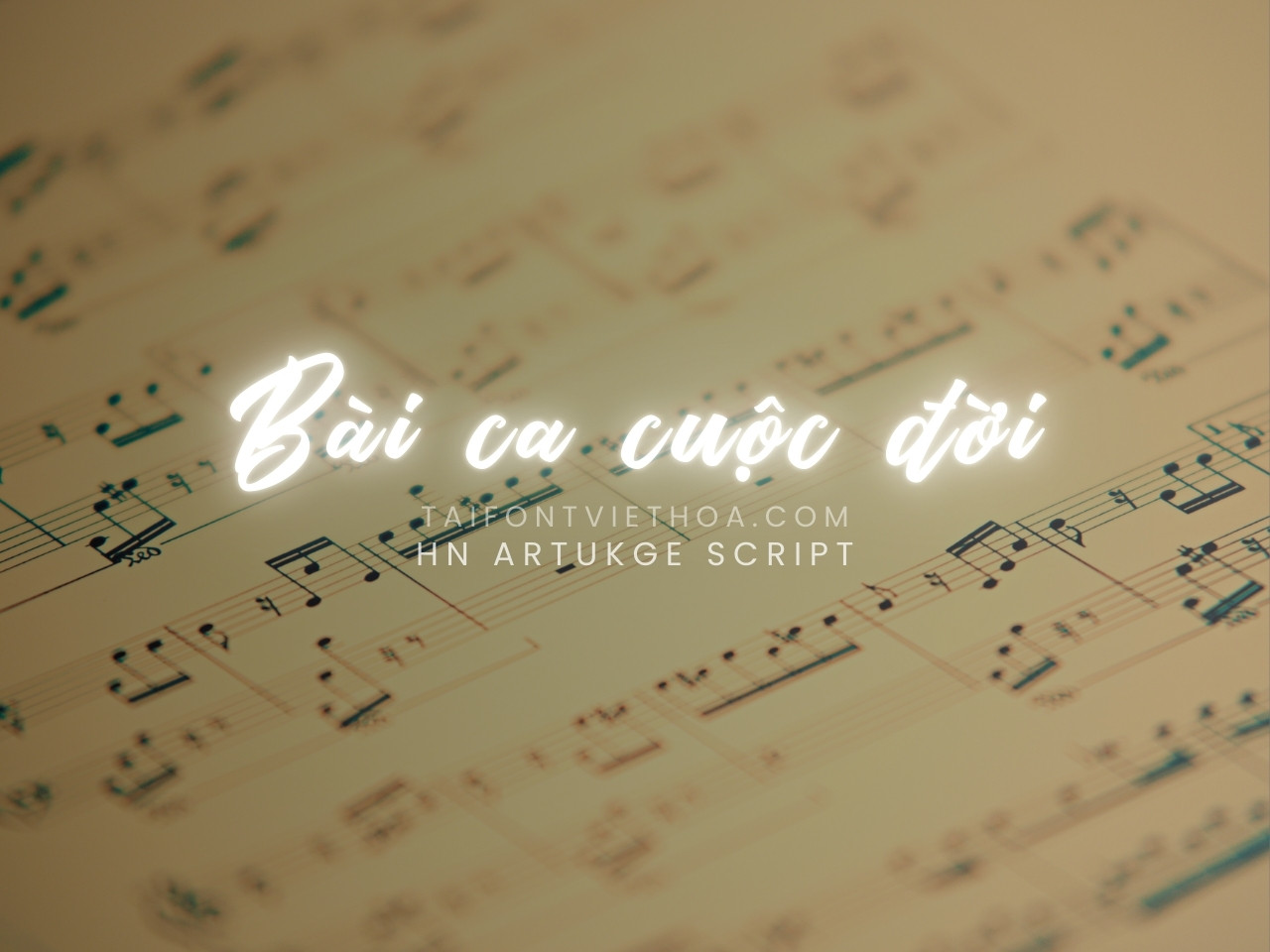
Giới thiệu font Artukge Script – Vẻ đẹp viết tay bay bổng từ Font Fabric
Artukge Script là một font chữ viết tay đầy cảm xúc được phát triển bởi Font Fabric Free – đơn vị thiết kế nổi tiếng chuyên cung cấp các font sáng tạo miễn phí chất lượng cao. Với kiểu dáng uốn lượn, mềm mại và mang tính cá nhân hóa cao, Artukge Script nhanh chóng chiếm được cảm tình của cộng đồng thiết kế trên toàn thế giới. Phiên bản Việt hóa do Huy Nam thực hiện đã hoàn thiện đầy đủ hỗ trợ tiếng Việt, đồng thời tương thích với hơn 100 ngôn ngữ khác. Font đã được taifontviethoa.com sưu tầm và chọn lọc để cung cấp đến cộng đồng người dùng Việt, đặc biệt phù hợp với các dự án cần yếu tố bay bổng, nghệ thuật và truyền cảm hứng cá nhân sâu sắc.
Thiết kế nghệ thuật và ứng dụng đa dạng của Artukge Script
Artukge Script sở hữu các đường nét uyển chuyển, thể hiện rõ tinh thần viết tay hiện đại với các nét nối liền tinh tế và hình dáng chữ mềm mại. Font mang đến cảm giác cá nhân, tình cảm và lãng mạn – rất phù hợp cho các thiết kế mang tính nghệ thuật như thiệp mời, thiệp cưới, tiêu đề blog, bìa sách hay sản phẩm truyền thông cho các dịp đặc biệt như Giáng sinh, lễ hội hoặc sự kiện cá nhân. Font còn bao gồm nhiều alternates và ligatures giúp tăng độ sáng tạo trong bố cục. Các ngành nghề phù hợp gồm: quảng cáo, ẩm thực, ảnh cưới, mỹ phẩm, handmade và nội dung truyền thông cảm xúc.